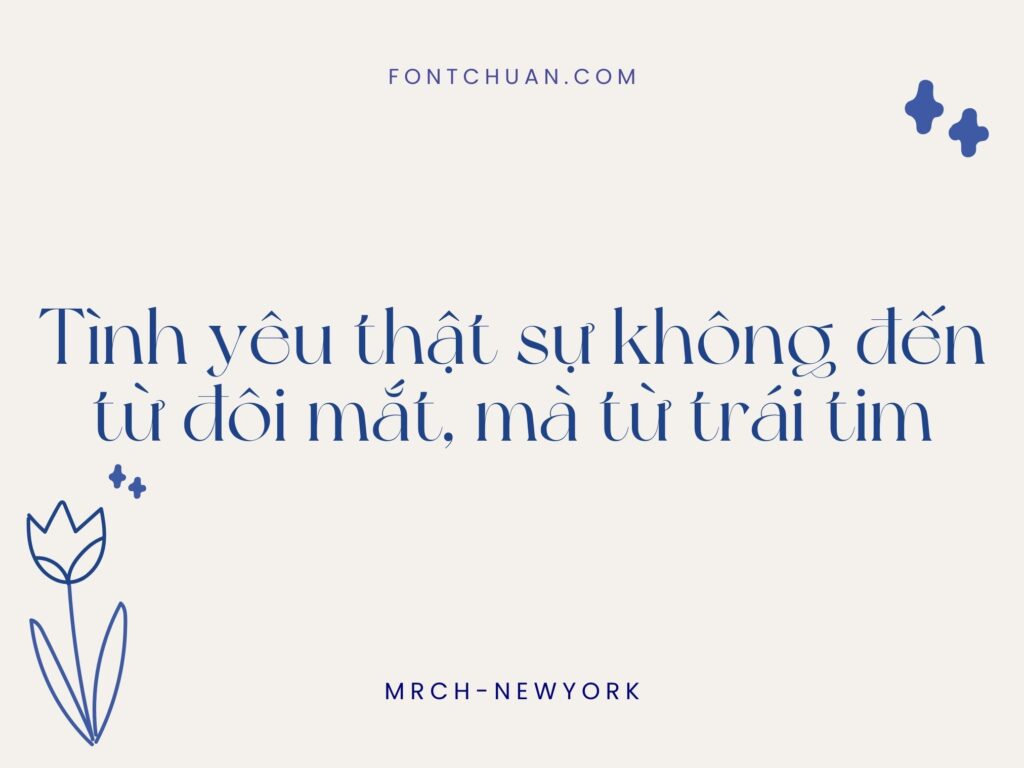
Font New York Việt Hóa
Tác giả Font: Artem Nevsky
Việt hóa bởi: March Nguyen
NewYork là một font serif hiện đại với độ tương phản cao, được thiết kế bởi Artem Nevsky. Font này mang đến vẻ đẹp thanh lịch và sang trọng, lý tưởng cho các dự án thiết kế cao cấp như thời trang, tạp chí, logo và thương hiệu. NewYork hỗ trợ hơn 200 ngôn ngữ dựa trên Latin, bao gồm cả tiếng Việt, và được sưu tầm và đăng bởi thành viên của Font Chuẩn.
Font có cấu trúc chữ rõ ràng, các đường nét tinh tế và độ dày nét đa dạng, tạo nên sự cân bằng giữa tính thẩm mỹ và khả năng đọc. NewYork phù hợp cho các thiết kế thiệp mời, logo, tiêu đề và các ấn phẩm truyền thông. Các ngành nghề như quảng cáo, thiệp cưới, giáo dục và bất động sản có thể tận dụng hiệu quả font này. Ngoài ra, NewYork còn rất thích hợp để làm Font chữ ảnh cưới, mang đến sự tinh tế, sang trọng và lãng mạn cho các bộ album, thiệp cưới hay các sản phẩm liên quan đến đám cưới. Ngoài ra, font cũng phù hợp cho các sự kiện như lễ hội, sinh nhật, ngày Nhà giáo và Valentine.